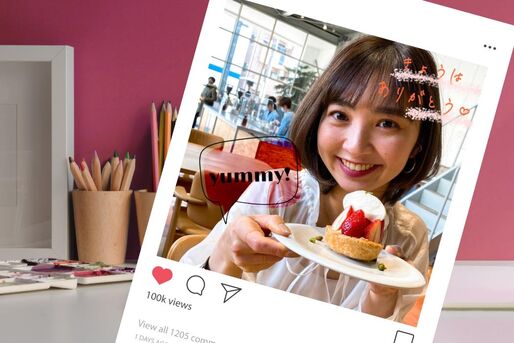
Instagramの加工テクニック「文字入れ」。おしゃれ&かわいいフォントを使って写真に文字入れするには、専用アプリを使うのがおすすめです。トレンドの無造作な手書きスタイルのひらがなや、被写体に合わせてカーブするように配置した文字などを使った画像も、専用アプリを使えば簡単に作成できるはずです。
アプリでさまざまな文字入れ加工が楽しめる
この記事では、初心者でも使える定番の文字入れアプリから、デザインに凝りたいユーザーも満足できる本格的な加工アプリまで、おすすめアプリ4本を使い方とともに紹介します。
【PicsArt】文字入れはもちろん、アート風加工に強いアプリ
「Picsart(ピックスアート)」では、文字入れのほかに吹き出し文字、アートなエフェクトやレイヤーの追加、手書き加工なども楽しめます。
吹き出しを使った文字入力もできる「PicsArt」の使い方
アプリを開いたら画面下の[+]ボタンをタップし、端末のアルバムから加工したい写真を読み込みます。続いて、画面下の[テキスト]から好きな文字を入力します。
文字を入力したら、好きなフォントに変更していきましょう。画面下の[フォント]を選択後、すぐ左上にある上ボタンをタップするとフォント一覧が表示されます。
フォントの横に王冠マークがあるものは、有料版で利用できる書体となります。ここでは「からかぜ」という大人っぽい手書き風のフォントを選びました。
文字は画面下の[色]ボタンでカラー変更なども可能。設定した右上の[適用]をタップしてください。
画面下のメニューを左スワイプすると表示される[吹き出し]では、おしゃれな吹き出しに好きな言葉を入力したスタンプが簡単に作成できます。写真のアクセントにもなるので、ぜひ使ってみてください。
アートなエフェクトやスタンプを使う
画面したのメニューにある[エフェクト]では、ぼかしやモノクロ、ノイズ系やカラー系のフィルターなどの加工が画像に施せます。
メニューの[ブラシ]は、キラキラやお花、星などをシールスタンプのように指でなぞって反映させる機能です。自分で好きな位置に、好きなだけ模様を追加できます。
フィードやストーリーのサイズに簡単トリミング
インスタ用の投稿を作るなら、フィードやストーリーのサイズにトリミングできる機能を使うのがおすすめ。
メニューにある[ツール]から[切り抜き]を選択したら、[フィード]や[ストーリー]など希望のサイズをタップしてください。自動的に適応サイズにトリミングしてくれます。
【Phonto】文字入れ加工の定番アプリ
アプリ「Phonto」
「Phonto(フォント)」は文字入れに特化した画像加工アプリで、200種類以上のフォントが利用可能です。そのうち、日本語フォントも30種類以上と豊富に用意されています。
日本語フォントにも対応する「Phonto」の使い方
アプリを開いたら画面下のカメラボタンをタップし、[写真アルバム]から加工したい写真を選択します。
フィルターの設定画面に遷移したら、好きなものを選び[完了]をタップ。次の画面で、読み込んだ画像の上をどこでもいいのでタップすると[文字を追加]のボタンが出てきます。ここを選択して、テキストを入力しましょう。
画面下の[フォント]をタップすると、好きな書体に変換できるようになります。日本語フォント一覧は、画面右下の[日本語]タブに切り替えて展開してください。
文字スタイル(カーブや透過文字など)の変更もできる
入力したテキストを再度タップすると、フォントの変更や色・サイズ・傾きなどの変更メニューが表示されます。
[スタイル]→[背景]の選択では、右の画像のように文字の背景を色の塗りつぶしでつけることが可能です(透明度なども調整できます)。
メニューを左方向へスワイプすると表示される[カーブ]は、入力した文字を最大で360度までカーブさせる機能です。被写体に合わせて文字をカーブさせるといった使い方ができます。
フィード投稿に便利、正方形トリミングも簡単
Instagramのフィード投稿に便利な正方形トリミングも、Phontoアプリなら簡単です。
画面左下のメニューボタンから[正方形化]を選んだら、位置調整やフィットスタイル(画面下の矢印ボタン)を調整してください。あとは[完了]ボタンをタップでOKです。
【Canva】細かい文字位置調整が自在&テンプレートも豊富
アプリ「Canva(キャンバ)」は、インスタグラムの投稿はもちろん、ロゴ、ポスター、名刺、招待状などのデザインを作成・加工できるアプリです。
スマホ・PCの両方で作成できる「Canva」の使い方
Canvaの魅力は、無料で自由度の高い加工ができること。おしゃれなフォントはもちろん、素材やテンプレートが充実しています。スマホとPC、どちらの環境でも作業ができるのもポイントです(ここではスマホで使用しました)。
Canvaを開き、右下の[+]ボタンをタップ。続いて「Instagramの投稿」あるいは「ストーリー」など、作成の用途に合わせてサイズを選びます。
設定できたら、画面下の「カメラロール」から加工したい写真・画像を選択してください。
次に画面下の[+]→[テキスト]で画面上部の[見出しを追加]をタップします。画像の上にテキストが表示されるので、タップして好きな文字を入力してください。
続いて画面下の[フォント]を選択すると、文字を好きな書体に変更できます。フォントの横に王冠マークがついているものは、有料版でのみ開放されます。
ストーリー、フィード専用のテンプレートが使える
Canvaにはデザイン性が高いテンプレートが揃っているので、それらを活用して投稿を作るのもいいでしょう。
画面右下の[+]ボタンから[Instagramの投稿]や[ストーリー]を選択すると、それぞれの投稿サイズに合ったテンプレ一覧が表示されます。
テンプレの画像を自分の写真に置き換えたり、不要な要素を削除したりすれば、元のデザインを活かした投稿が作れます。
テキスト部分はタップで編集が可能です。フォントや位置などはそのままに、文字だけ打ち替えるといいでしょう。
フォントや写真の位置を上下左右に微調整
スマホアプリ版Canvaを利用するとき、指で文字や写真の位置を調整するのには限界があります。そこで便利なのが「微調整」機能です。
動かしたい要素(フォント部分や画像など)をタップした状態で、画面下の[微調整]メニューを選択。あとは、表示された上下左右の矢印で好きな方向に少しずつ位置をずらしていくだけ。全体のバランスを整えるのに役立ちます。
【PhotoDirector】かわいい文字入力、コラージュ、フィルター加工まで
アプリ「PhotoDirector」は、文字入れ加工だけではなく、コラージュや背景加工にも対応しています。アプリを開くと、サブスクリプション画面に切り替わりますが、画面左上の[<]戻るボタンをタップすれば無料版のまま使用可能です。
個性的な日本語フォントが光る「PhotoDirector」の使い方
ホーム画面の[編集]を選択し、加工したい画像を端末のアルバムから読み込みます。続いて画面下の[テキスト]をタップしてください。
テキストは2タイプあります。シンプルにテキストを入力する場合は[テキスト]を、吹き出しやハートなどの囲みを追加したい場合は[テキスト吹き出し]を選んでください。今回は、[テキスト吹き出し]からハートのデザイン吹き出しを選んでみました。
テキスト部分をタップすると、文字の編集ができるようになります。好きな文字を入力後、画面下の[フォント]から書体を変更してください。フォント左側に「Try」の印がないものなら、無料版で自由に使えます。
複数の画像をコラージュできる、おしゃれなテンプレ
PhotoDirectorでは、複数の画像を1つのテンプレートにまとめて配置できます。シンプルな文字入れ加工だけではなく、ストーリー投稿にもぴったりなテンプレートを使ってコラージュ加工もできるというわけです。
ホーム画面にある[コラージュ]ボタンから好きなテンプレートをタップし、コラージュしたい画像を複数選べば自動で配置されます。
おしゃれなカラーフィルターは濃度調節も可能
画面下のメニューから[エフェクト]をタップすると、さまざまな種類のエフェクト一覧が表示されます。
おすすめは「ルック」機能。おしゃれなフィルターの種類も豊富で、簡単に濃度調整もできます。投稿の雰囲気を決めるフィルター加工までPhotoDirectorアプリで完結できるため、重宝するでしょう。